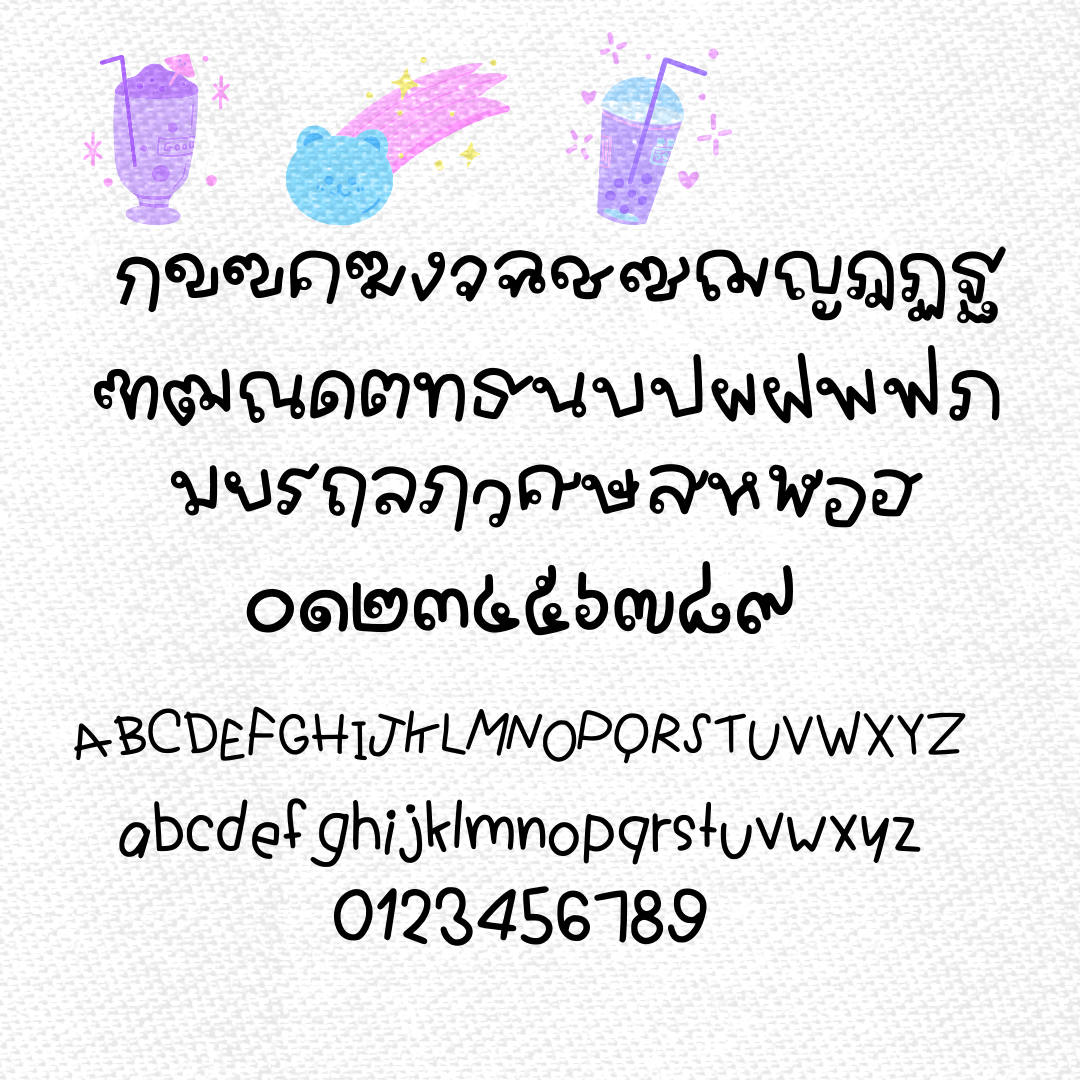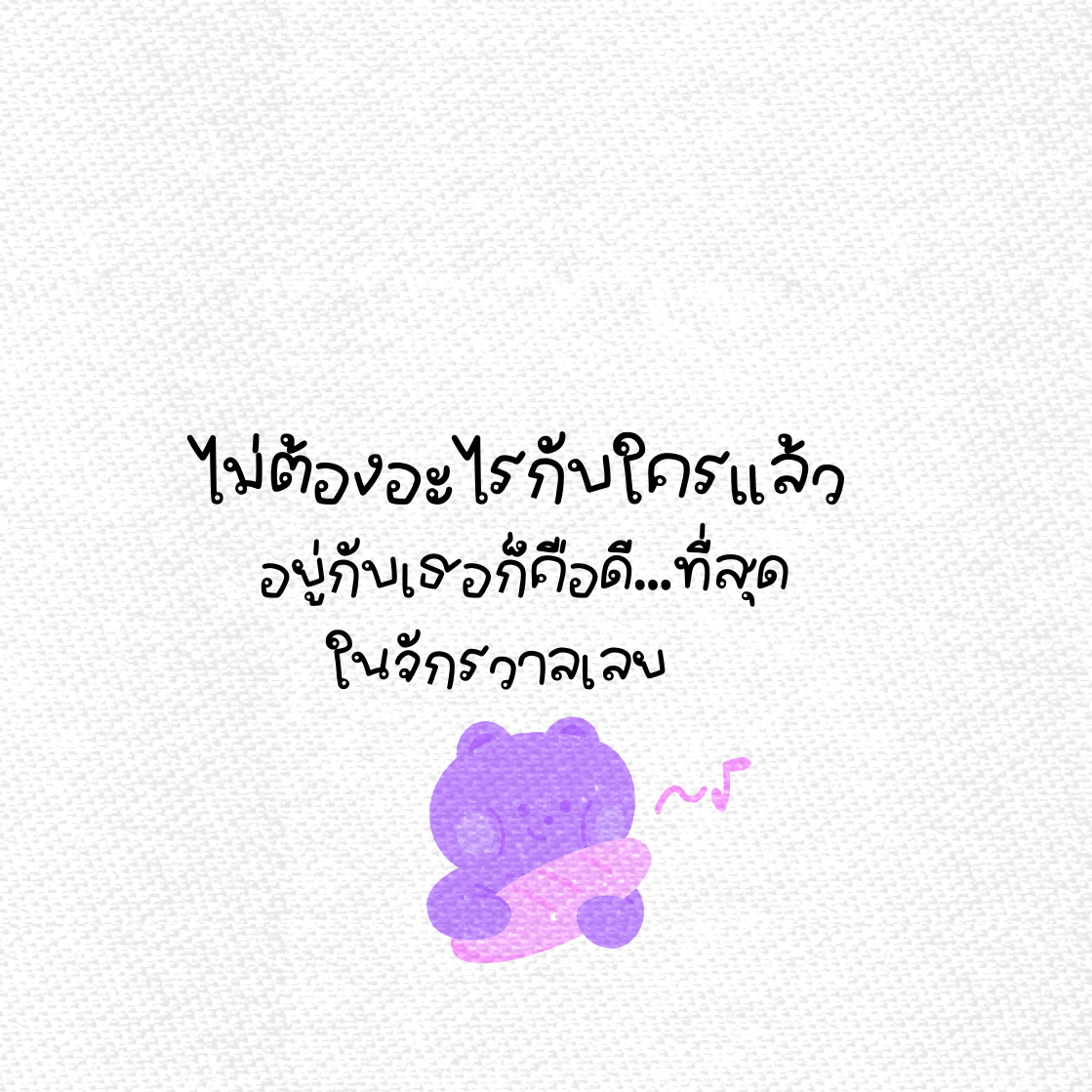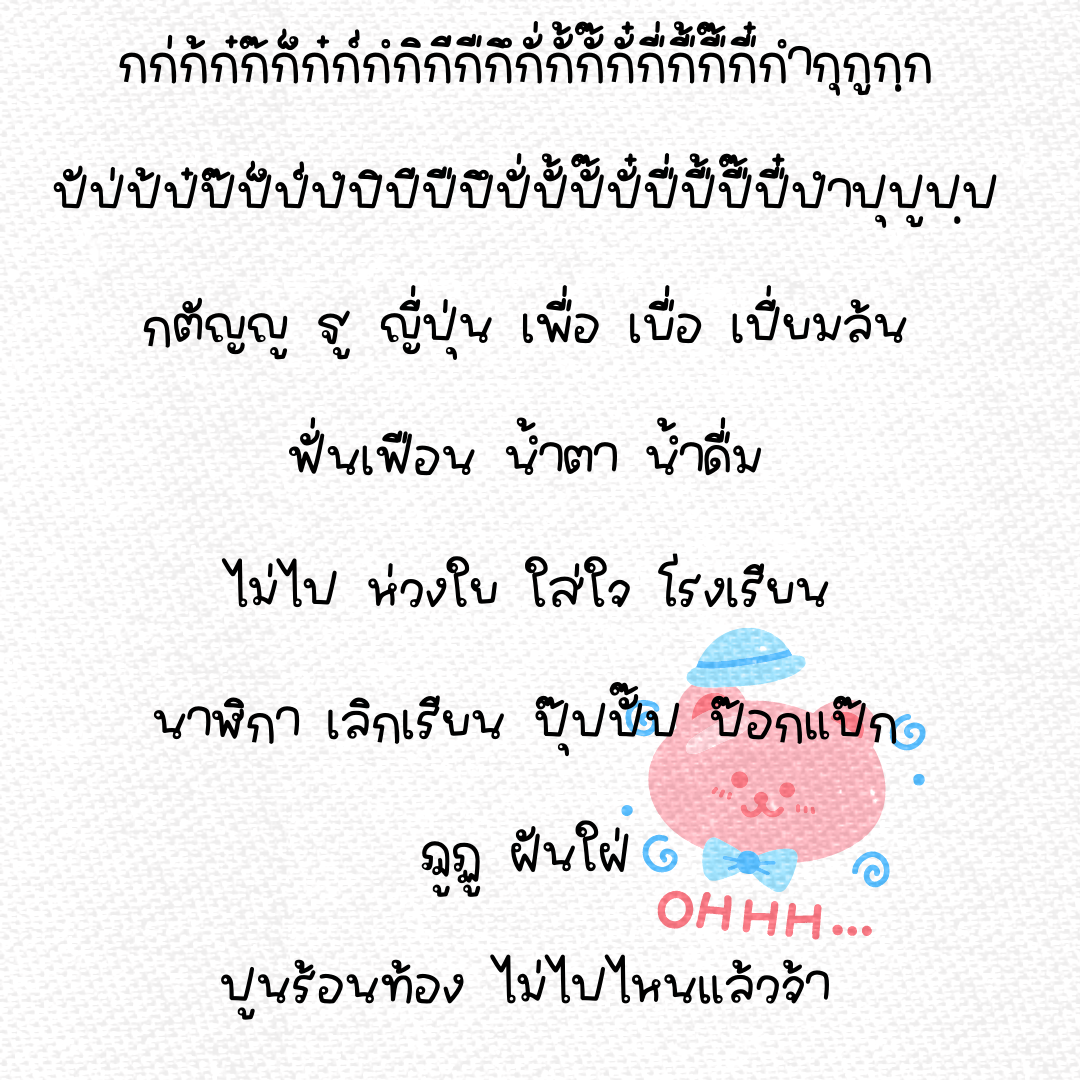
ฟอนต์นูร่าโยย่า (nura yoya font)
ฟอนต์ลายมือ เหมือนลายมือเด็กน้อย ฟอนต์มีความสนุก เหมือนไม่ตั้งใจเขียน ฟอนต์มีด้วยกันสองเวอร์ชั่น แบบธรรมดา และแบบตัวอักษรเอียงแบบไม่เป็นระเบียบ